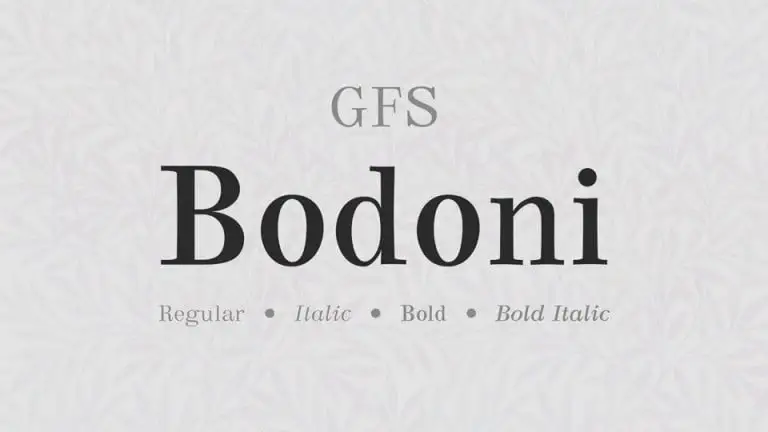
GFS Bodoni Serif Font
A GFS Bodoni Serif Font é uma fonte serif que traz à tona um estilo elegante e contemporâneo ideal para design gráfico moderno. Com x-tamanho médio-alto, ela se destaca especialmente para títulos e identidades de marca, oferecendo uma graça casual em seu aspecto de tipografia. Este tipo de fonte foi criado pela Greek Font Society baseada em um antigo design italiano da época do século XVIII, projetado pelo impresor e tipógrafo Giambattista Bodoni. Perfeita para quem busca um equilíbrio entre clássico e atualidade, a GFS Bodoni Serif é uma escolha ideal tanto para designers de marca quanto para aqueles buscando um toque de sofisticação em seus projetos visuais.